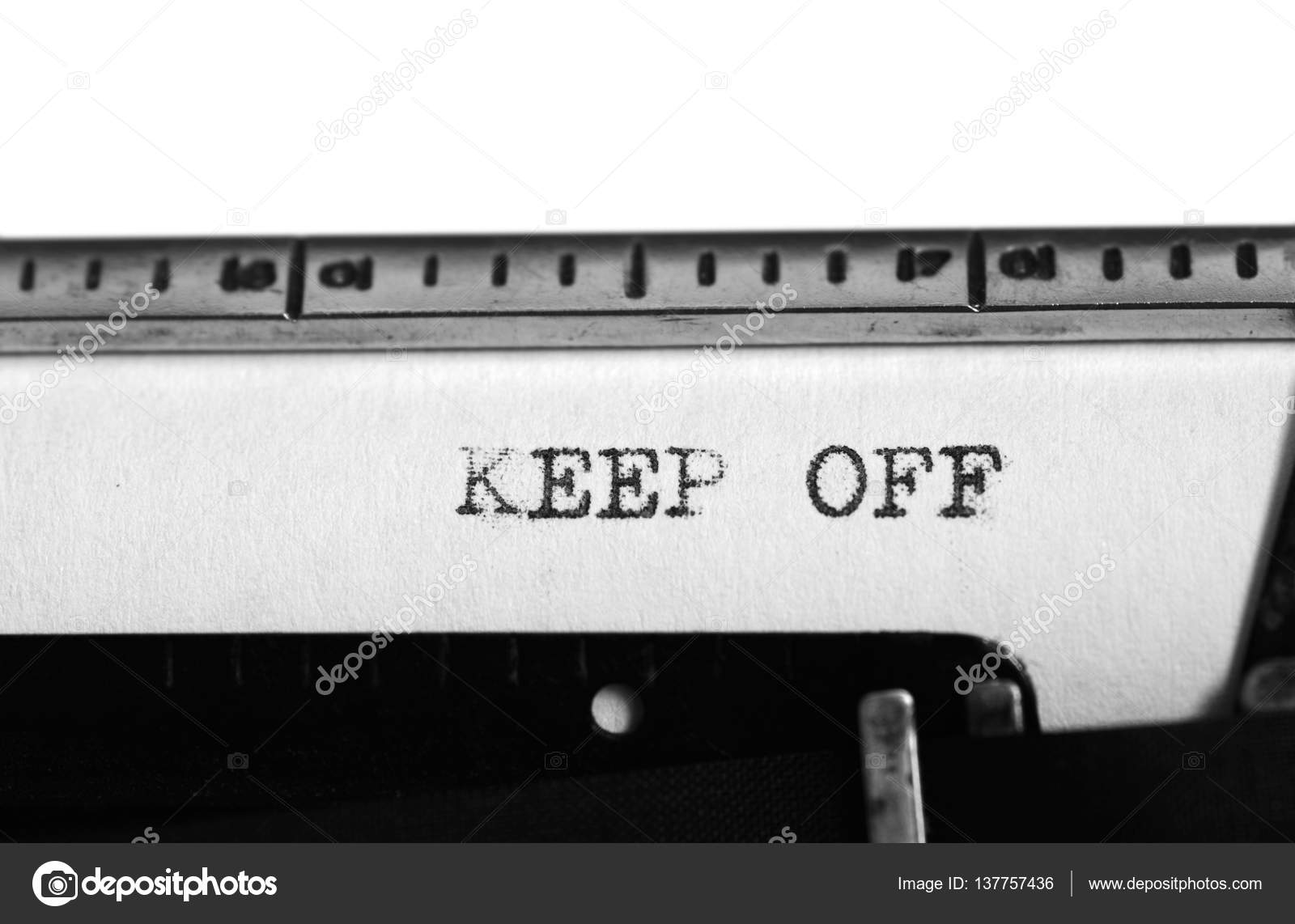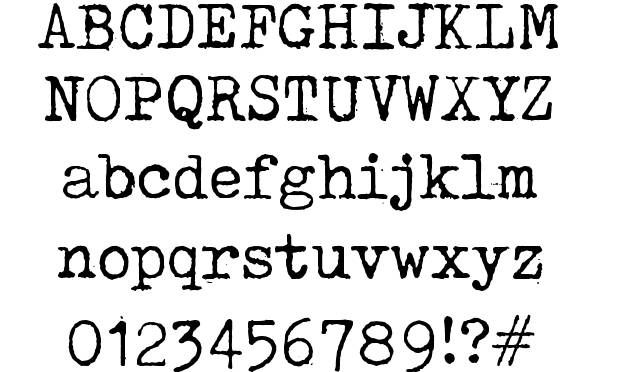
Конвертер писем для пишущих машинок ➡️ Конвертер писем для пишущих машинок
Пишущая машинка конвертер букв. к открывать разные источники для Instagram откройте приложение, напишите или вставьте свой контент, просмотрите его в разных форматах, скопируйте отрывок с нужным шрифтом и вставьте текст в Instagram, Facebook, Twitter, Youtube, WhatsApp, Twitch, TikTok или любая социальная сеть. Есть и другие места, которые также предлагают эту услугу.
Поскольку Instagram Stories предлагает определенные возможности, когда мы пишем описания, комментарии или сообщения, нет возможности, кроме шрифта по умолчанию.
Тем не менее, есть сторонние инструменты которые предлагают пользователям возможность размещать другие источники. Продолжайте с нами, чтобы узнать больше об этой альтернативе и узнать, как используйте шрифты, которые делают ваши публикации более привлекательными, в данном случае конвертер писем от пишущей машинки.
Пишущая машинка конвертер букв. Если вам нужны дополнительные параметры для оформленного текста, просто нажмите «загрузить больше шрифтов». Возможности, которые появляются здесь, более случайны, они немного отличаются от стандартных и объединяют ресурсы, которые имеют мало общего, смайлики и символы.
[Конвертер букв пишущей машинки] ➡️ Как использовать собственные шрифты?
Instagram и другие социальные сети устанавливают шрифт, который лучше всего соответствует общему стилю системы.
Это часть единообразия, необходимого для визуального комфорта пользователей, просматривающих эти платформы.
— Конвертер букв машинки. Оказывается, есть способ добавить стилизованные буквы, которые на самом деле являются специальными символами, а также смайлики и другие символы. На практике они выглядят как пользовательские шрифты, но технически их называют
Поскольку этот совет для многих еще недавний, он отличная возможность быть замеченным в социальной сети и кто знает, получить последователей В Instagram. Не говоря уже о том, что люди будут чувствовать Любопытно посмотреть, как вам удалось таким образом изменить шрифт.
Поэтому некоторые классные приложения для этих шрифтов в Instagram можно настроить биографию профиля или выделите части подписей к фотографиям и видео, которые вы публикуете. Это творческие способы улучшить вашу стратегию цифрового маркетинга.
Помня, что эти источники следует использовать экономно, в основном для выделить важные части например, название вашей компании, специальные предложения по публикациям для получения выгоды от продаж, заголовок текста или раздела и т. д.
Пишущая машинка конвертер букв. Какими бы забавными они ни были, чрезмерное их использование может создать впечатление, что ваша учетная запись слишком случайна.
Но используйте шрифты индивидуально сбалансированный стандартные шрифты хороши, если они разборчивы и эстетически соответствуют вашему бренду. Кстати, это очень важно для тех, кто использует Instagram в компаниях или влиятельных лицах.
1. Откройте инструмент
Чтобы упростить процесс, мы рекомендуем использовать шрифты на том же устройстве, на котором вы получаете доступ к Instagram.
2. Напишите или вставьте свой текст
Второй шаг — написать или вставить в поле текст, в котором вы собираетесь применить настраиваемый шрифт.
Когда вы вводите или вставляете слова, отобразит список вашего стилизованного фрагмента в разных шрифтах. Если вам нужны дополнительные возможности, просто нажмите «загрузить больше шрифтов».
3. Скопируйте отрывок с желаемым шрифтом.
Помните, что в Instagram нет возможности редактировать источник. Что мы сделаем, так это сохраним последовательность символов, а затем перенесем их в нужное поле.
Поэтому выберите отрывок с тем шрифтом, который вы хотите использовать, и используйте команду копирования на вашем устройстве.
4. Instagram, Facebook, Twitter, Youtube, WhatsApp, Twitch, TikTok или любая социальная сеть.
Теперь, когда ваш текст сохранен в буфере обмена вашего ПК или телефона, используйте команду вставьте биографию, описание, комментарий или сообщение.
Пишущая машинка конвертер букв. Помните, что может возникнуть некоторая несовместимость символов Unicode. Следовательно, убедитесь, что фрагмент отображается так, как ожидалось И если да, отрегулируйте его, чтобы не удивлять своих подписчиков.
Наконец, мы рекомендуем вам выбрать один или два из этих шрифтов для частого использования, чтобы они
Поэтому попробуйте использовать шрифты, чтобы сделать подписи к изображениям более красивыми. Помните, что визуальная привлекательность в Интернете очень велика, и использование его в дословной части содержания привлечет больше внимания к вашему сообщению.
Некоторые из немногих на том сайте выглядят моноширинными и имеют достаточно полные наборы знаков в кодировке ASCII, включая DELEGATE, FOSTER, KING, REMINGTON, TOXICA. Однако ни один из них не имеет расширенного набора знаков, и ни один не отмечен как моноширинный, так что они не могут использоваться в текстовых редакторах или как шрифты для броузеров. Однако, некоторые из них могут оказаться полезными.